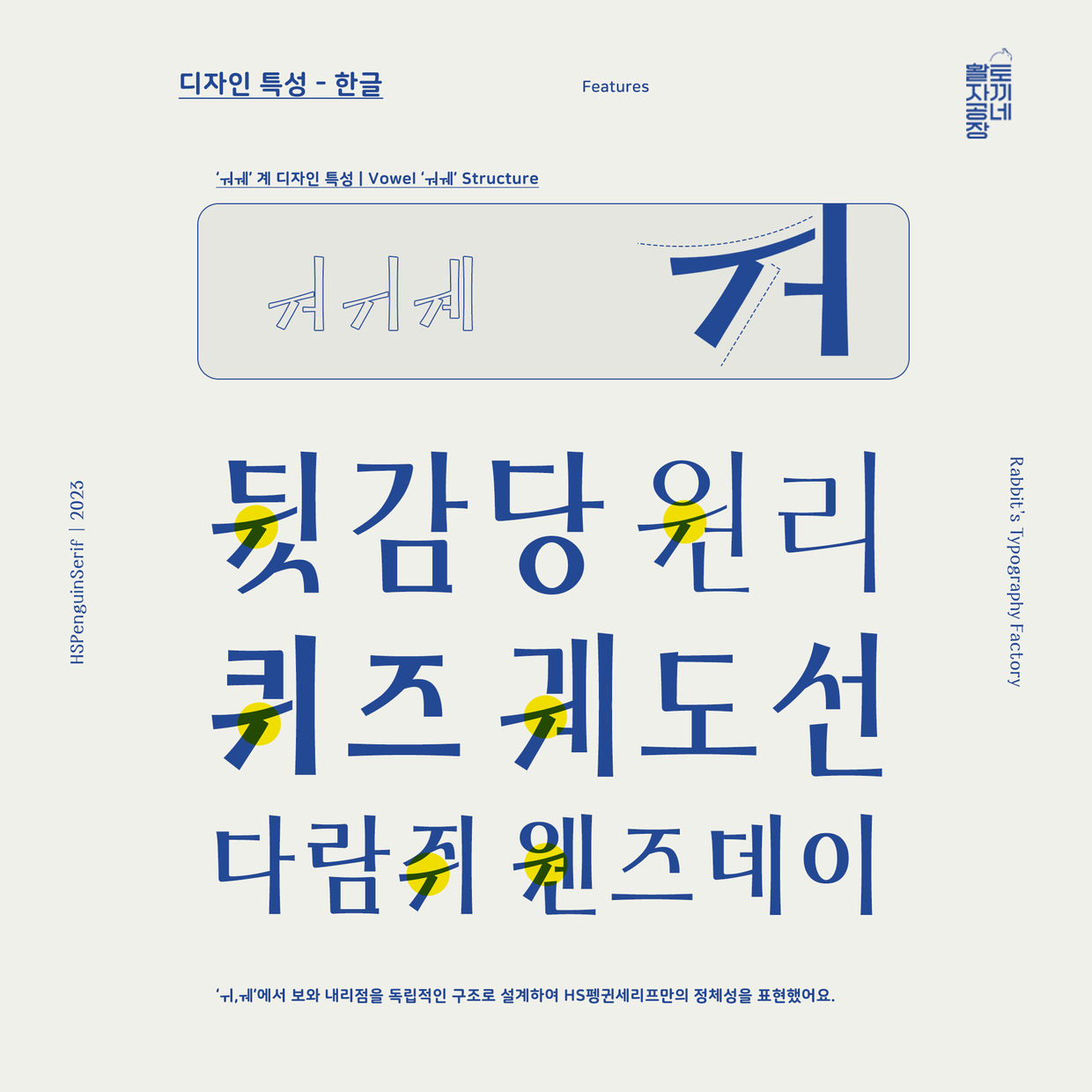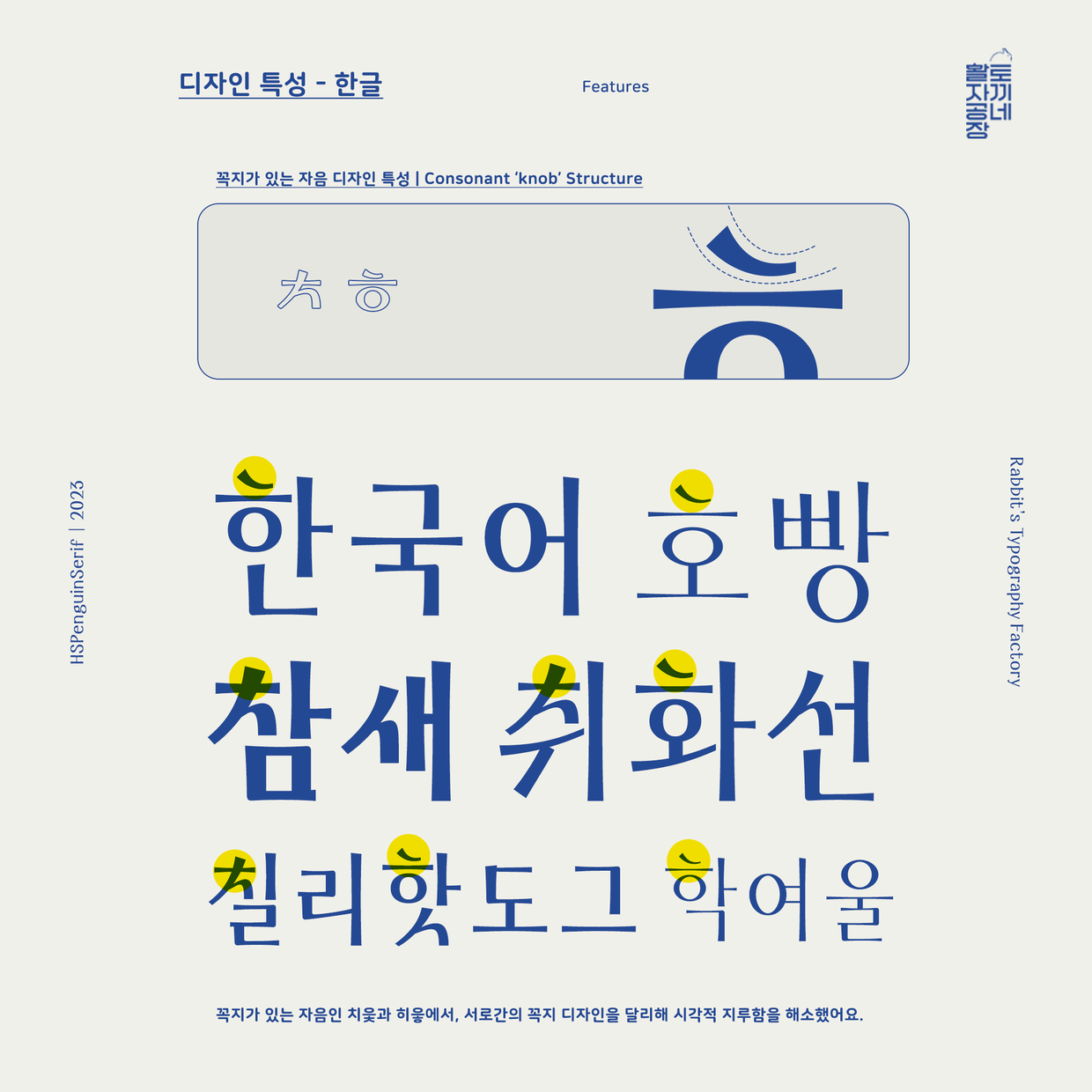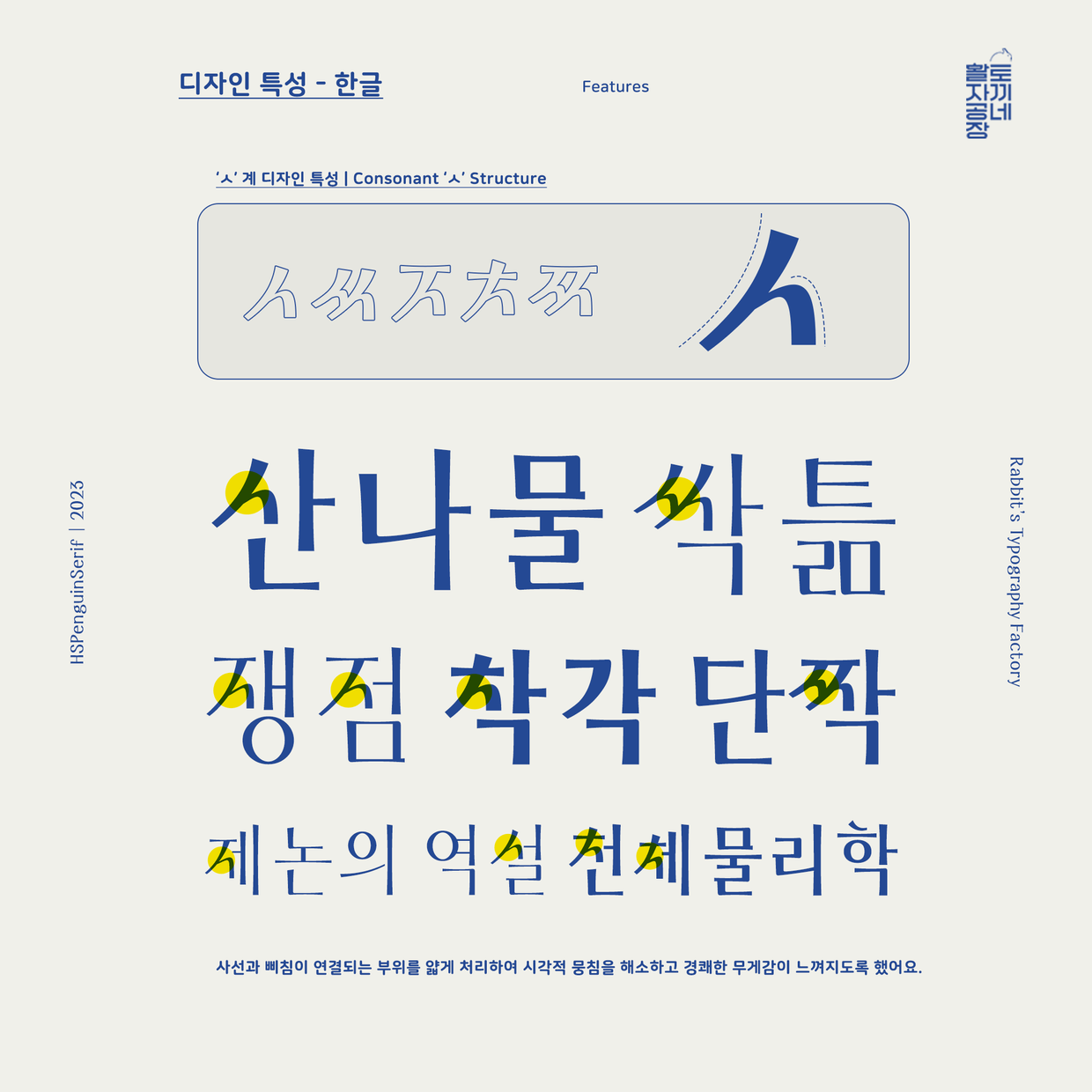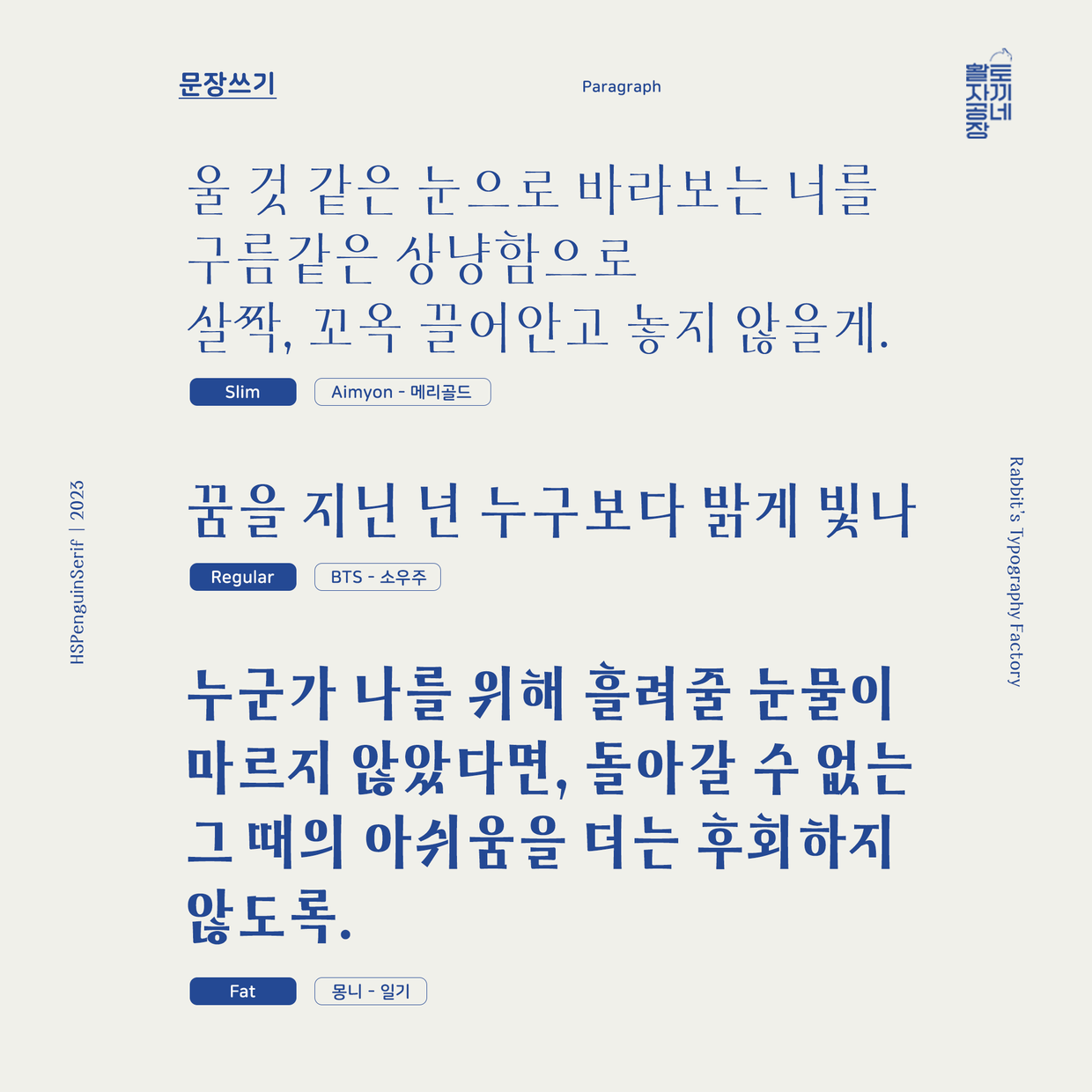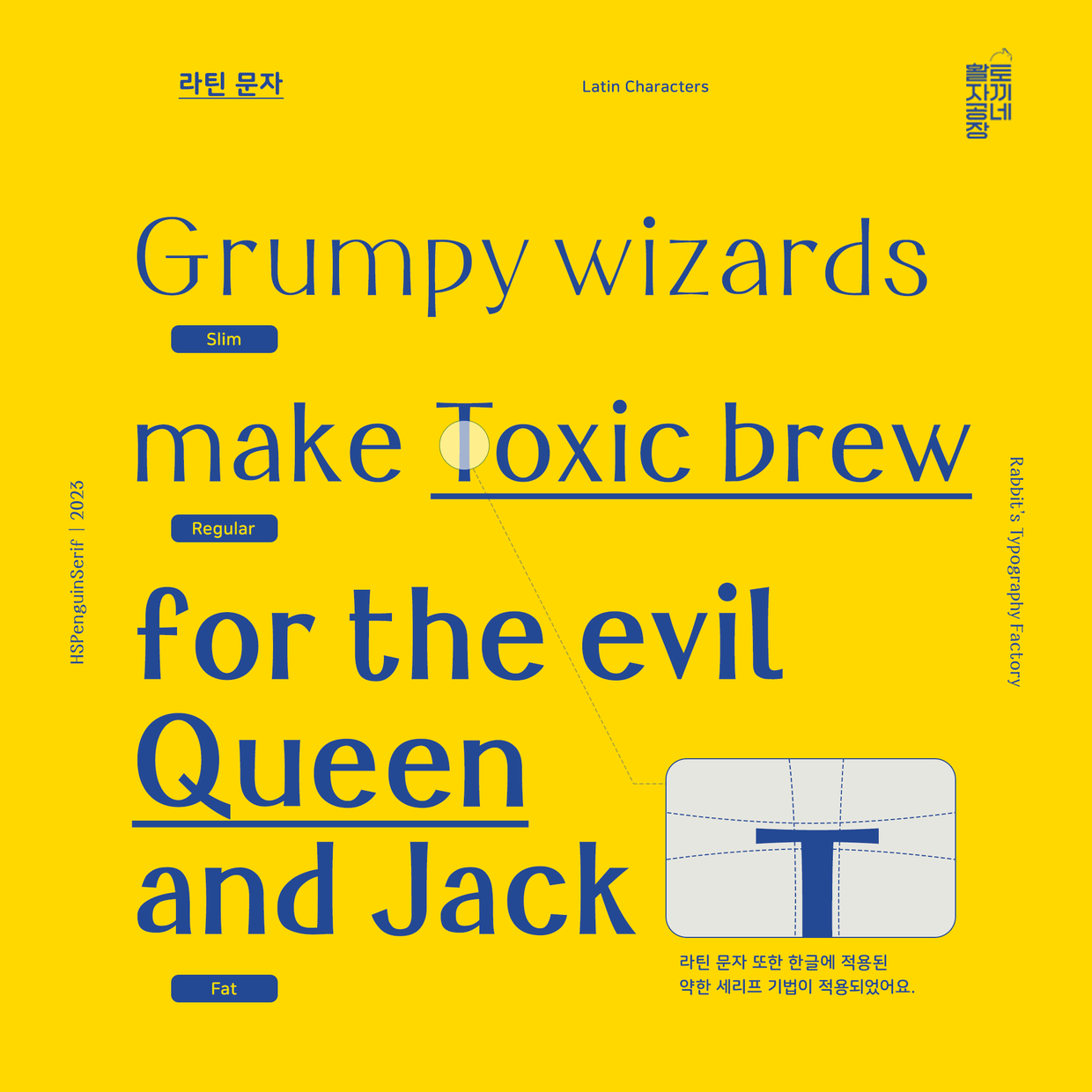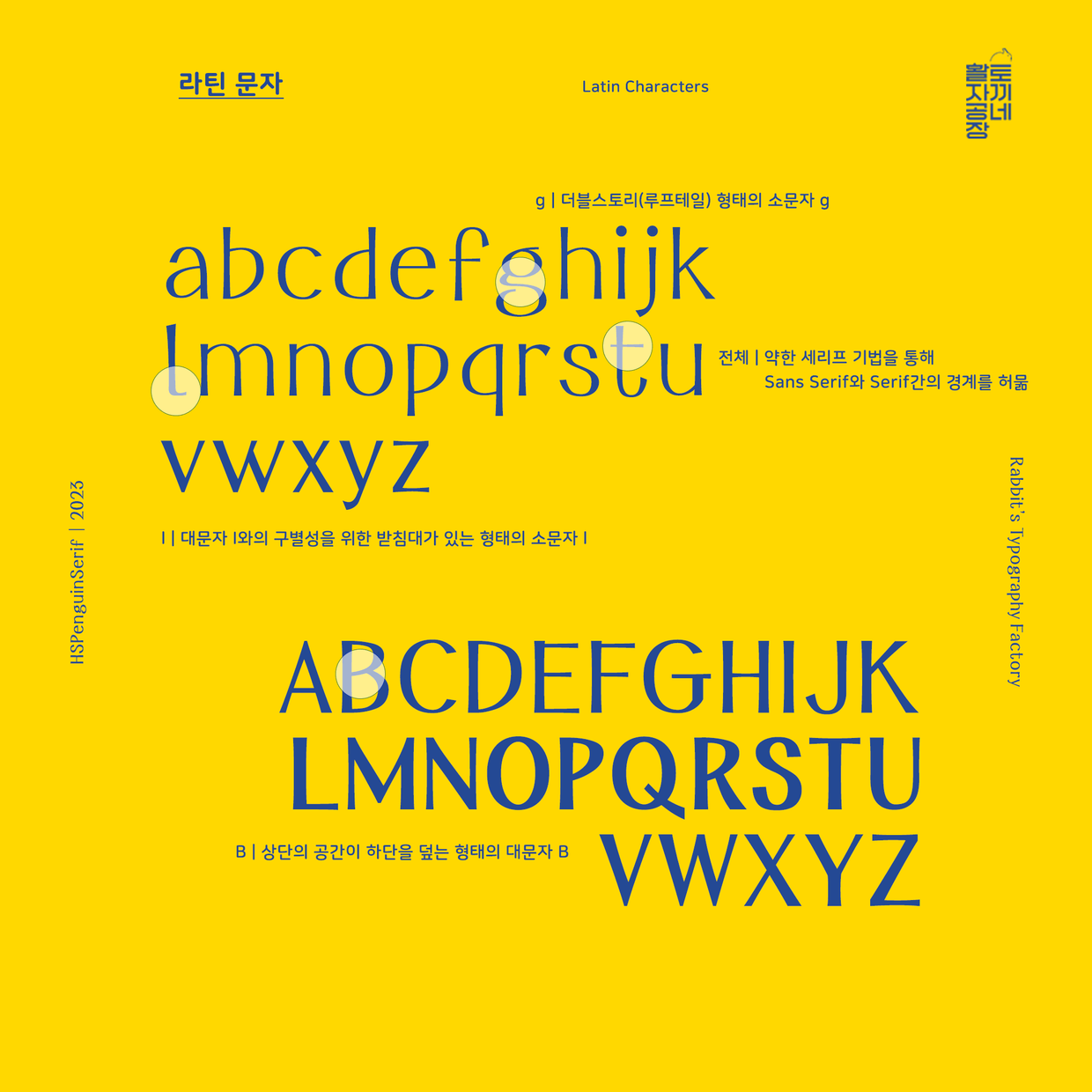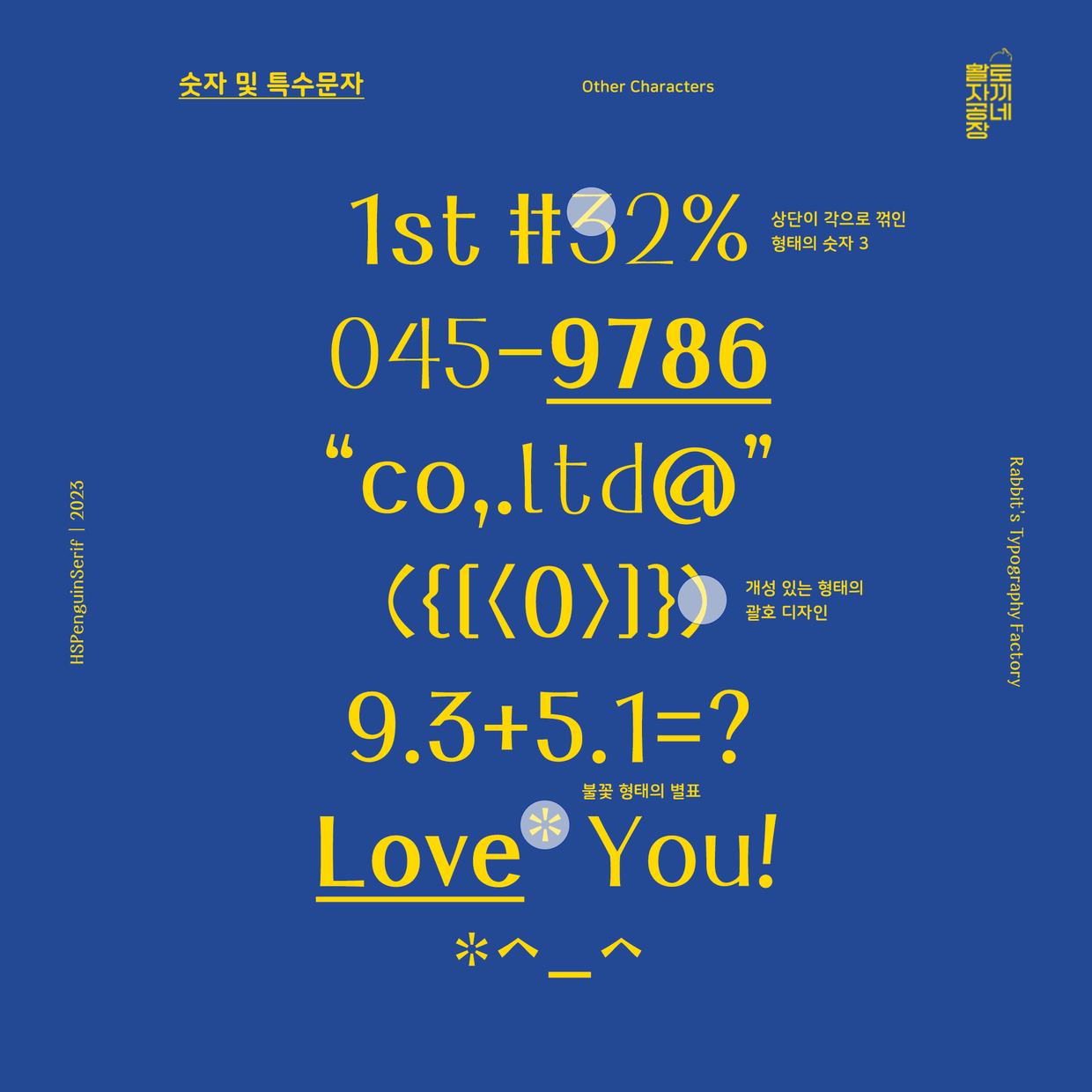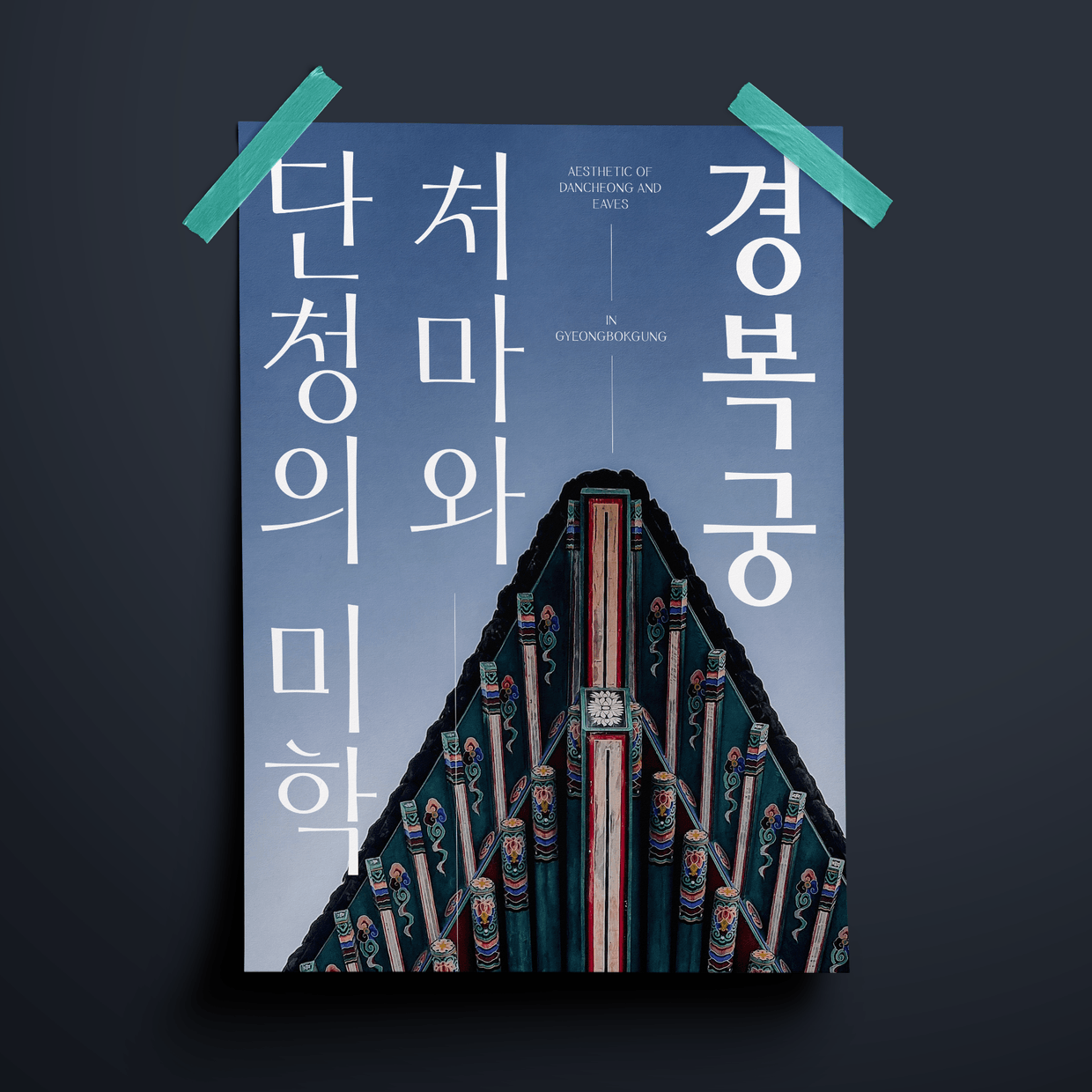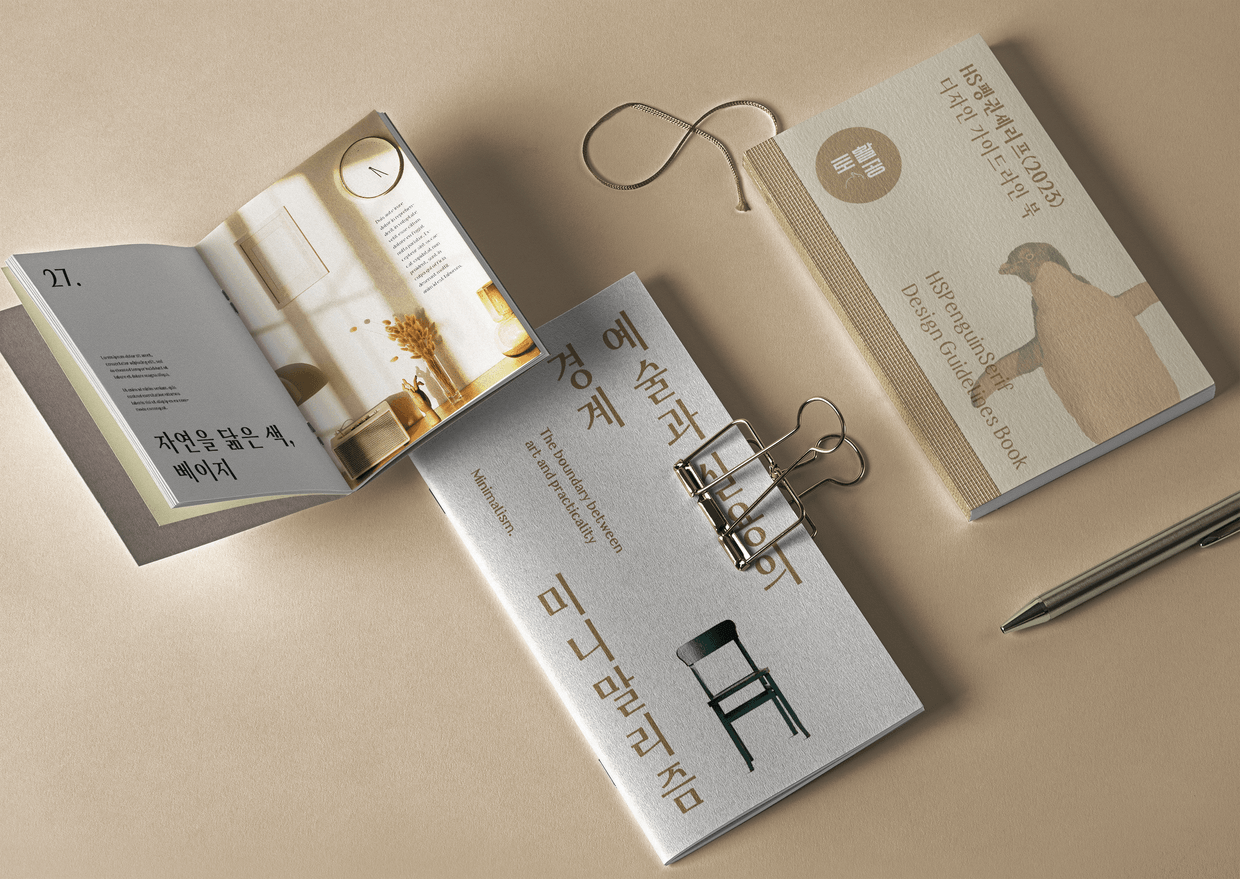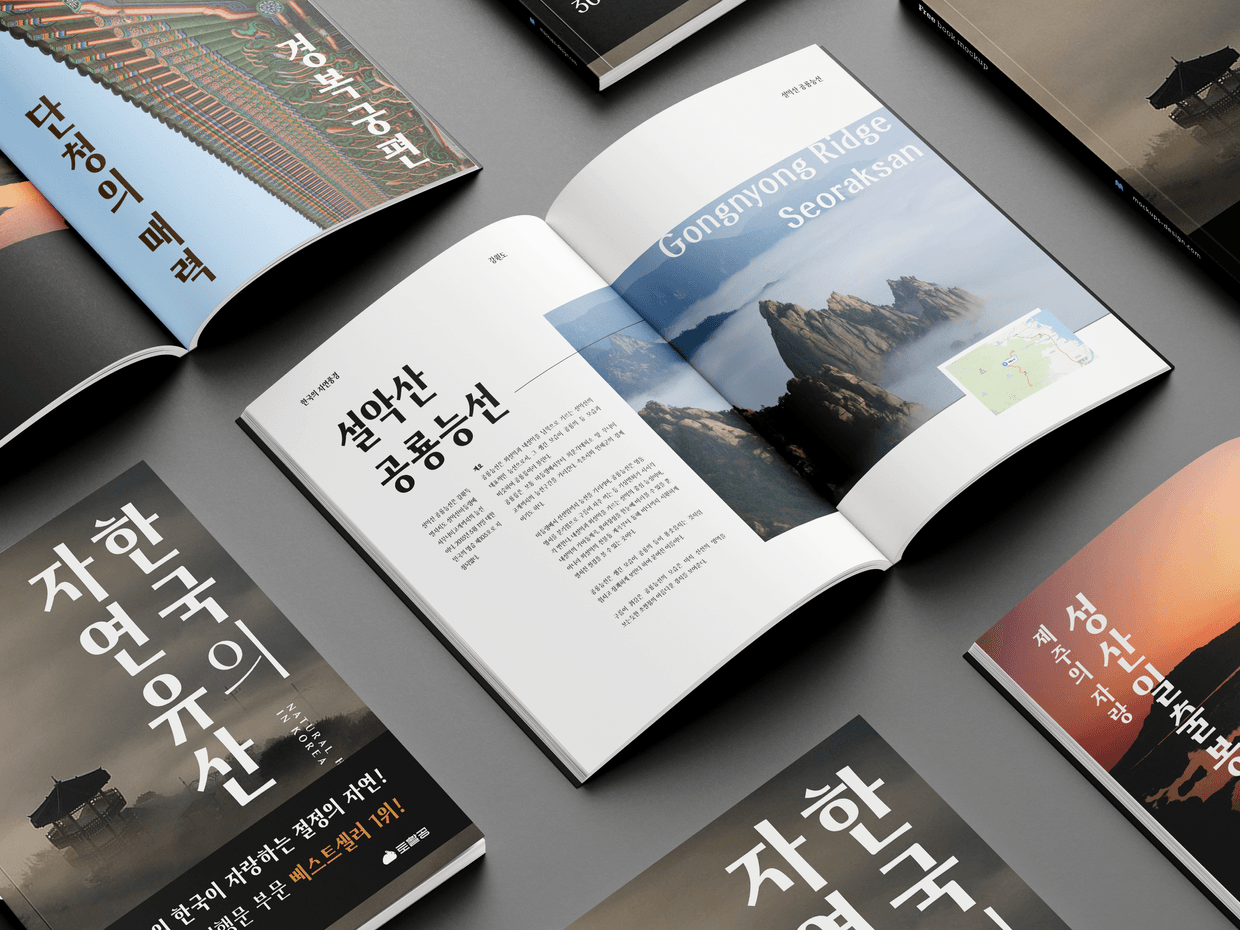
HS펭귄세리프(2023)는 토활공 역사상 최초로 외래어로 작명된 한글 서체 작품이자, 최초로 명칭에서 '-체'라는 접미어가 사라진 작품입니다.
이번 펭귄 프로젝트에서는 3가지 굵기에 대한 디자인적 통일성의 관용도를 낮춘다면 어떤 결과가 도출될지에 대한 실험이 있었습니다. 실험 결과, 세 굵기의 부분적인 조형이 통일되지 않더라도 패밀리로서의 위상이 떨어지지 않음을 확인할 수 있었습니다. 이러한 예측 실험이 적중한 것을 기념하기 위해 상용 폰트로의 작품으로 제작했습니다.
HS펭귄세리프(2023)는 명확한 세리프보다는 약한 세리프를 첨가해 세리프체와 산 세리프체의 경계를 모호하게 했습니다. 이를 통해 진지함과 가벼움을 동시에 표현할 수 있도록 의도했습니다.
동물 펭귄의 외형이 세로로 길다는 것에 착안하여 서체의 쉐입 또한 세로로 긴 형태로 표현해 타 서체와의 조형적 차별성을 두었습니다.
이번 HS펭귄시리즈는 3개의 굵기를 두어 활용성을 극대화했으며, Regular를 기준으로 얇은 서체는 Slim, 굵은 서체는 Fat으로 지칭하여 날씬한 펭귄, 표준의 펭귄, 뚱뚱한 펭귄이 연상되게끔 하는 익살스러움을 더했습니다.